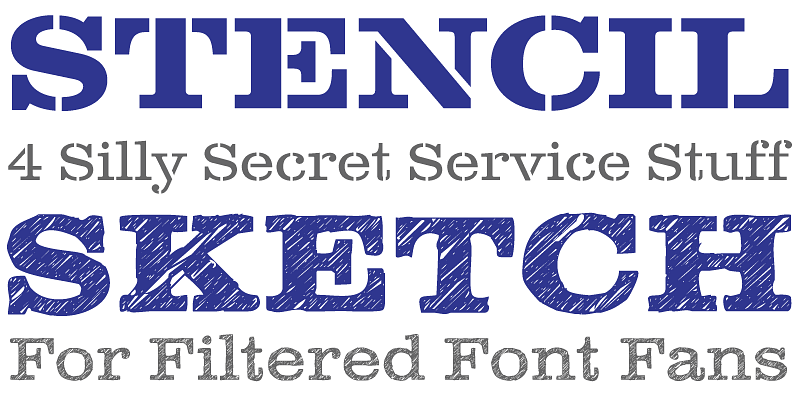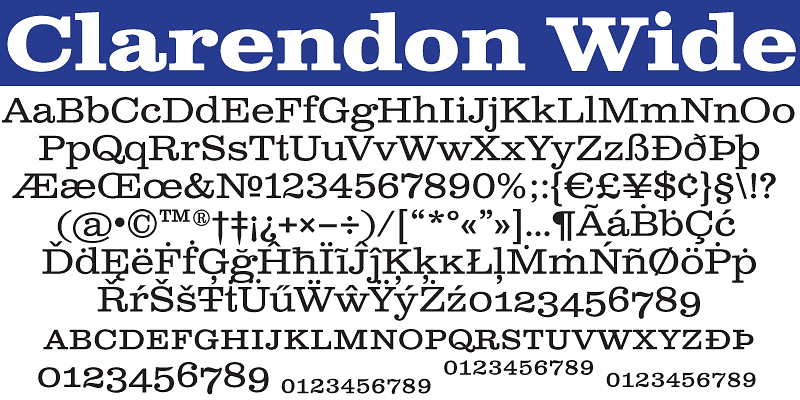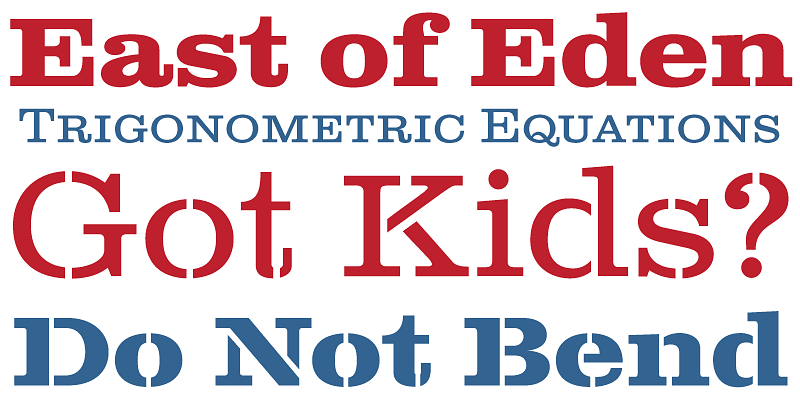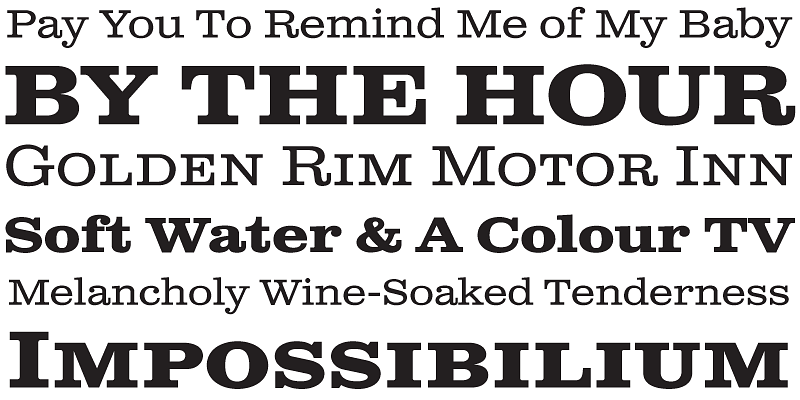
Questo è l’ampio compagno di visualizzazione della famiglia Clarendon Text. È disponibile in dieci stili: normale, medio, grassetto, con maiuscoletto e controparti di figure vecchio stile, oltre a versioni stencil e sketch degli stili normale e grassetto.